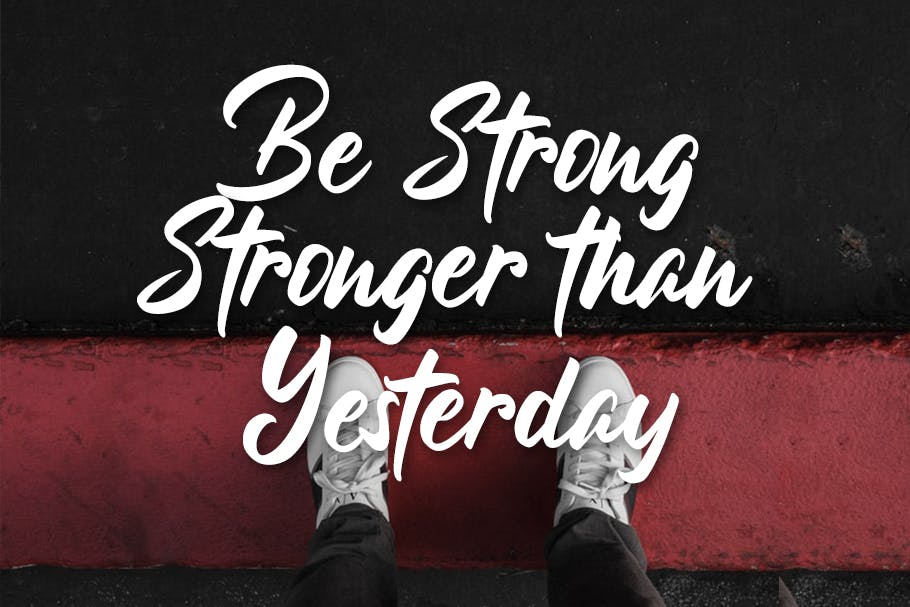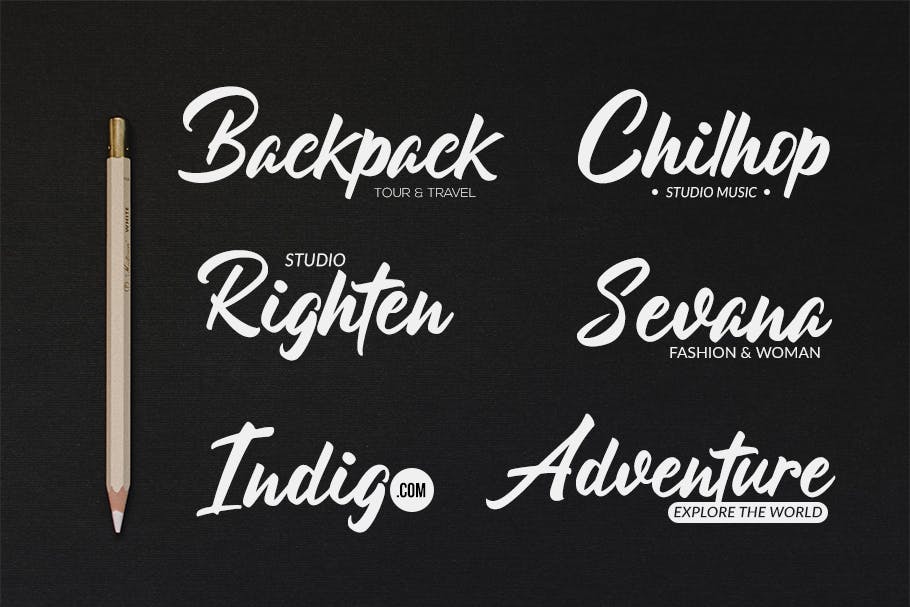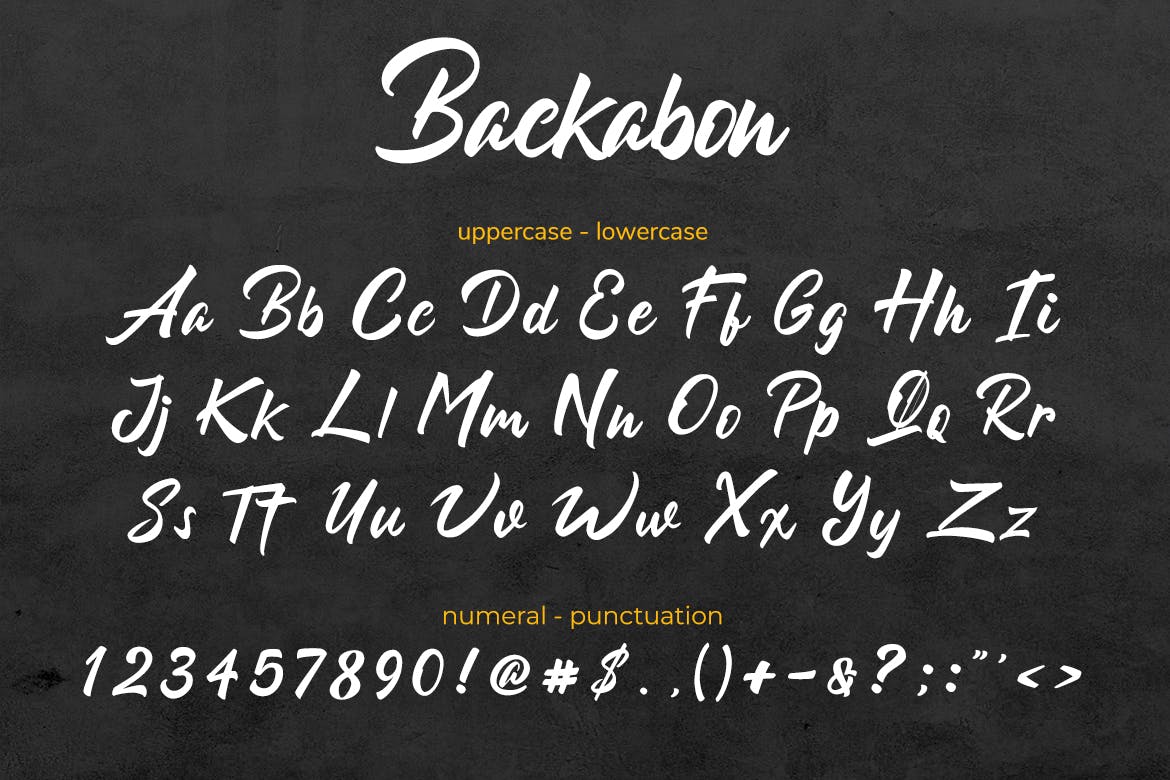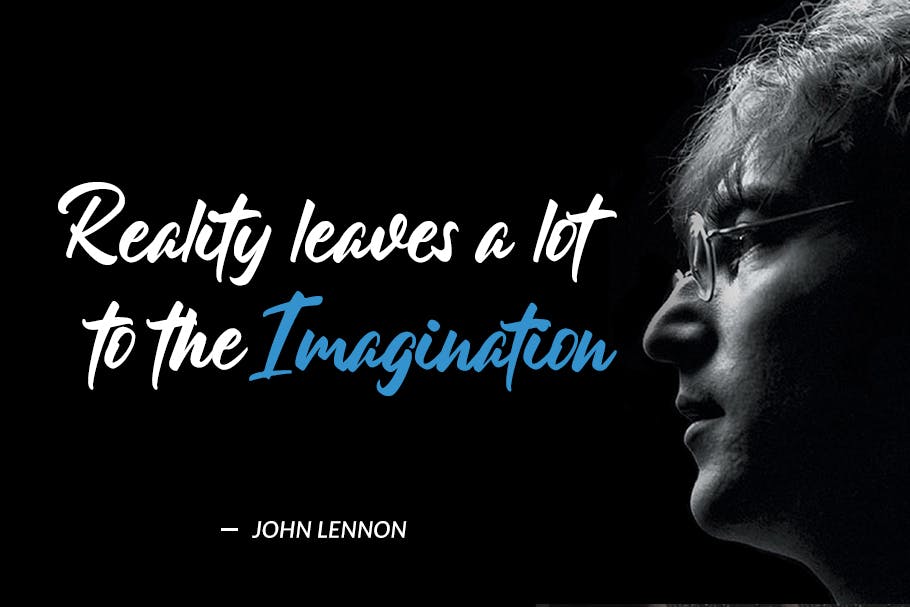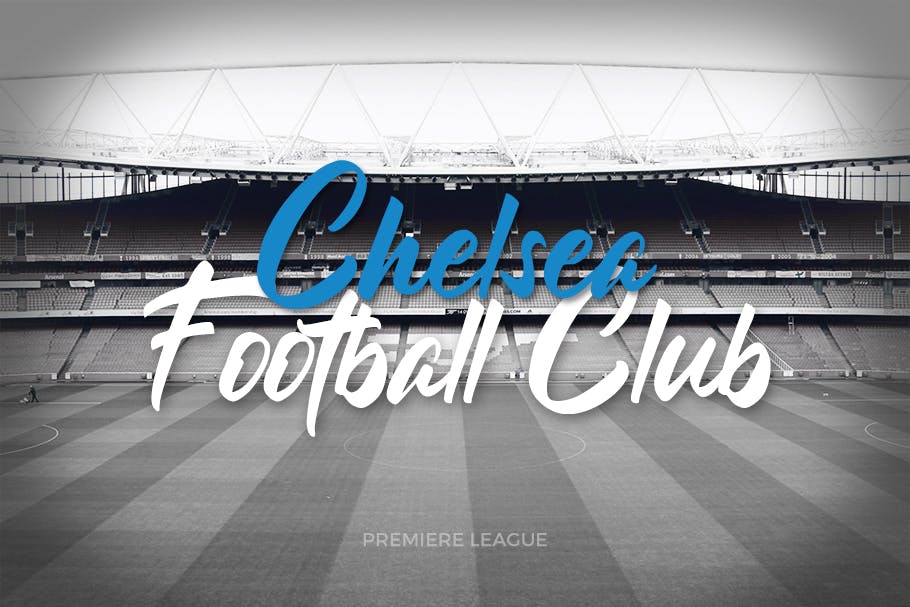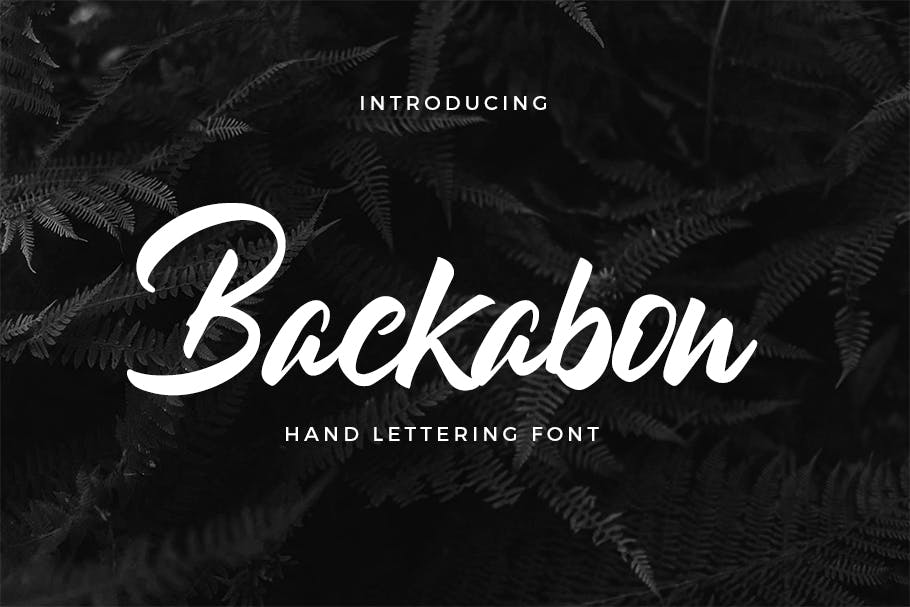
دانلود فونت دست‌نویس Backabon برای طراحی‌های خلاقانه
Backabon Hand lettering Font
فونت Backabon با طراحی جذاب و مدرن، مناسب برای پروژه‌های خلاقانه شماست.
فونت Backabon یک فونت اسکریپت متصل وBold است. این فونت برای پروژه‌های خلاقانه شما مانند لوگوها، نقل‌قول‌های چاپی، دعوت‌نامه‌ها، کارت‌ها، بسته‌بندی محصولات، هدرها، لوگوتایپ، سربرگ، پوستر، طراحی لباس، برچسب و غیره بسیار مناسب است.